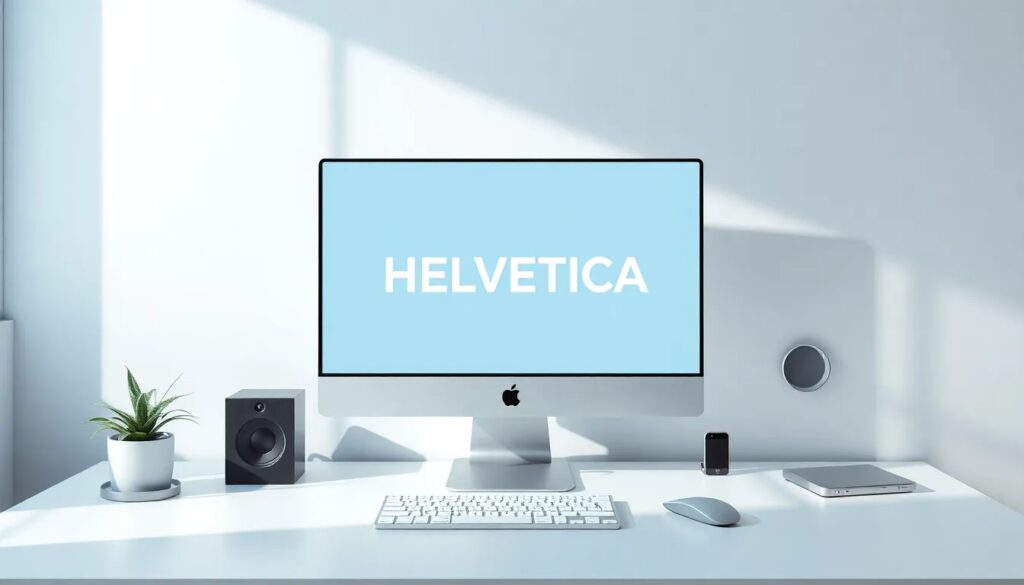
Helvetica google font: mejores alternativas gratuitas
La tipografía es un elemento clave en el diseño gráfico y web, y elegir la fuente adecuada puede marcar la diferencia en la percepción de una marca. Una de las fuentes más icónicas y utilizadas es la Helvetica, conocida por su claridad y elegancia. En este artículo, exploraremos las alternativas gratuitas a la Helvetica Google Font, sus características y su historia, así como recomendaciones para su uso en diseño web.
Fuentes Google similares a Helvetica
La Helvetica Google Font es una opción popular, pero hay varias alternativas que ofrecen características similares y son totalmente gratuitas. A continuación, exploraremos algunas de las mejores opciones disponibles en Google Fonts.
- Roboto: Esta fuente sans-serif es moderna y versátil, ideal para interfaces de usuario.
- Open Sans: Con su diseño legible, es perfecta para sitios web y aplicaciones móviles.
- IBM Plex Sans: Combina elegancia con una estética contemporánea, adecuada para proyectos profesionales.
Cada una de estas fuentes tiene un estilo distintivo que puede adaptarse a diferentes necesidades de diseño, asegurando que tu proyecto mantenga una apariencia profesional y atractiva.
¿Cuáles son las mejores alternativas gratuitas a Helvetica Google Font?
Cuando se busca una alternativa a la Helvetica Google Font, es importante considerar no solo la estética, sino también la funcionalidad. Aquí te presentamos algunas de las mejores opciones gratuitas.
- Montserrat: Con una amplia gama de estilos, Montserrat es ideal para encabezados y textos destacados.
- TeX Gyre Heros: Esta fuente ofrece un aspecto similar a Helvetica y es perfecta para documentos y presentaciones.
- Source Sans Pro: Diseñada para ser fácil de leer en pantalla, es una buena opción para textos largos.
Estas alternativas garantizan que puedas lograr un diseño limpio y profesional sin incurrir en costos adicionales.
¿Qué características tiene la fuente Helvetica?
La Helvetica es famosa por su claridad y neutralidad. Algunas de sus características más destacadas son:
- Diseño sans-serif que mejora la legibilidad.
- Espaciado equilibrado entre letras.
- Amplia variedad de pesos y estilos, desde ultraligero hasta negrita.
Estas propiedades hacen que sea una opción popular para logotipos, señalización y productos impresos. Al utilizarla, los diseñadores pueden transmitir un mensaje profesional y contemporáneo.
La versión actualizada, Helvetica Neue, mejora la legibilidad y el espaciado, convirtiéndose en una opción versátil para diversas plataformas. Para utilizarla en tu sitio web, puedes seguir estos pasos:
¿Cuáles son otras fuentes de Google similares a Helvetica?
Además de las mencionadas anteriormente, hay otras fuentes en Google Fonts que comparten similitudes con la Helvetica. Considera las siguientes opciones:
- Poppins: Ideal para títulos y textos cortos, con un estilo geométrico.
- Noto Sans: Diseñada para ser legible en varios idiomas, es perfecta para proyectos globales.
- Raleway: Una fuente elegante que funciona bien para encabezados y diseños sofisticados.
Estas fuentes ofrecen una excelente alternativa a la Helvetica Google Font y pueden adaptarse a diversas necesidades de diseño.
- Fira Sans: Ideal para aplicaciones móviles, ofrece una buena legibilidad.
- Avenir: Con un estilo moderno, es perfecta para aplicaciones y sitios web contemporáneos.
- Ubuntu: Diseñada específicamente para la interfaz de usuario, proporciona un diseño amigable.
¿Cuál es la historia de la fuente Helvetica?
La Helvetica fue diseñada en 1957 por Max Miedinger en Suiza y se ha convertido en un símbolo del diseño moderno. Su nombre deriva de la palabra latina para Suiza, "Helvetia". Desde su lanzamiento, ha sido utilizada por empresas de renombre y organizaciones gubernamentales.